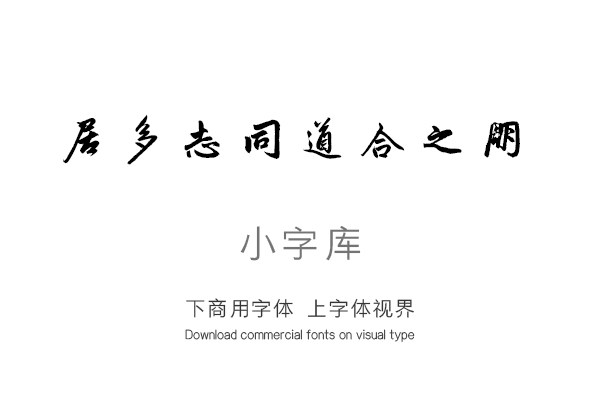
《汉标赵孟頫送瑛公住持隆教寺疏卷》一款根据元代赵孟頫《送瑛公住持隆教寺疏卷》,经过再次调整制作的小字库,该小字库共收录了该真迹作品中约223个字体。单字授权
兹审石室书记瑛公住持昌国州隆教禅寺,凡我与交,同词劝处西湖之上,居多志同道合之朋;歌白石之章,遂有室迩人远之叹。第恐大瀛之小刹,难淹名世之俊流。石室长老禅师,学识古今,心忘物我。江湖风雨,饱饮诸方五味禅;棒喝雷霆,显扬圣谛第一义。扫石门文字之业,传潜子书记之灯。鈯斧既已承当,瓣香须要着落。望洋向若,不难浮尊者之杯;推波助澜,所当鼓烝徒之楫。即腾阔步,少慰交情,开法筵演海潮音,龙神拱听,向帝阙祝华封寿,象教常隆。至治元年十二月日疏。松雪道人书。